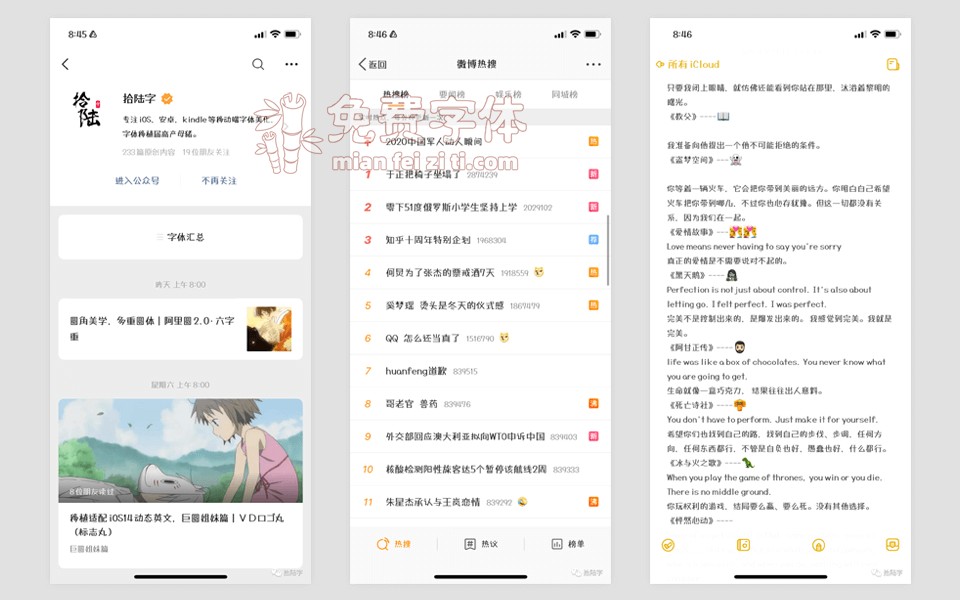
Tanugo漫画体是@拾陆字发布的一款基于Tanugo手写体进行字数补全的免费商用手写字体。根据作者@拾陆字的介绍,原版其实有4个字重,但是利用原版字重来进行补字是十分头疼的,因为目前并没有类似风格的大字库可以补这款字。只能弯道超车,利用原版regular字重为模板,然后用两款黑体大改,尽量接近Tanugo。然后再重新渲染制作独立的粗体以及细体字重。
此版字风格十分可爱,且长文排版阅读舒适感也不错。官版其实还有一个圆角化版本,喜欢的可以关注@拾陆字的微信公众号进行私信留言,人数多了博主@拾陆字便自己改造一版。